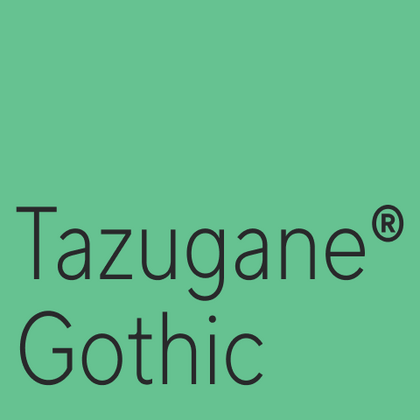
Шрифты похожие на Tazugane® Gothic
В этой подборке наши гарнитуры-альтернативы полностью заменят шрифт Tazugane® Gothic. Если вам близок его гибридный характер, обратите внимание на наши версии — они сохраняют фирменные черты — асимметричные кривые и динамичные пропорции. Эти альтернативы идеальны для проектов на стыке культур: брендинг с восточной эстетикой, интерфейсы международных сервисов или упаковка премиум-товаров.
Если вы устали от «заезженных» шрифтов и ищете гарнитуры, похожие на Tazugane® Gothic, ознакомьтесь с нашими лучшими альтернативами Tazugane® Gothic. Это шрифты, которые имеют близкие характеристики, но в то же время обладают новыми уникальными особенностями дизайна. Например, относятся к той же категории шрифтов, подходят для тех же целей и имеют похожие черты, но отличаются в деталях или пропорциях.
Найдите отличную замену Tazugane® Gothic и попытайтесь имитировать похожее настроение, передать нужное вам ощущение, используя его в своих проектах. Каждый шрифт, представленный на этой странице, является двойником шрифта Tazugane® Gothic, фактически его полным аналогом.
TT Chocolates — изящный гуманистический гротеск сo сбалансированными пропорциями, близкими к классическим. Шрифт с приятным дружелюбным характером, который интуитивно воспринимается как что-то знакомое.
TT Ricordi Greto — неконтрастный флорентийский гротеск с динамичными пропорциями. Это единственный гротеск среди антикв в коллекции TT Ricordi, при этом в нем сохранились едва заметные засечки, отсылающие к прототипу.
TT Firs Neue — скандинавский гротеск, сочетающий выразительные графические элементы с универсальностью использования. Мы проанализировали каждый контур и графический элемент. Пересобрали шрифт заново, чтобы сохранить лучшее и исправить необходимое.
TT Fellows — гуманистический гротеск с механистическими мотивами. Открытые формы, дружелюбно-нейтральный характер тонких весов и ещё более мягкий характер в жирных начертаниях.
TT Ramillas — стильная и современная антиква. Включает уникальные декоративные начертания и буквицы с цветочным орнаментом.
TT Octosquares — октагональный гротеск с футуристическим характером. Этот шрифт отличается геометричностью и своеобразной «мозаичностью»: он как бы собран из отдельных фрагментов, что проявляется и в мельчайших деталях.
TT Firs Text создавался на основе обновленной в 2023 году гарнитуры TT Firs Neue. Мы сохранили эстетику скандинавского минимализма, но полностью перерисовали все выразительные элементы, сделав их более мягкими и традиционными.
TT Norms® Pro — один из самых востребованных шрифтов студии, выбор известных мировых брендов. Более трёх переизданий за семь лет, первые строчки на MyFonts, десятки кастомизаций. Это «рабочая лошадка», которая станет незаменимой базой любой шрифтовой коллекции.
TT Commons™ Pro — один из самых востребованных шрифтов студии. Сфера его применения практически безгранична! Беспроигрышный вариант для тех, кто ищет стильный и функциональный базовый шрифт для любых проектов.
TT Hoves Pro — скандинавский гротеск с нейтральным, но в то же время узнаваемым характером. Это удобный и функциональный, при этом стильный и эстетичный инструмент для дизайнеров. Такой шрифт позволит вам решать множество разноплановых задач!
TT Supermolot Neue — непобедимое оружие в борьбе за стиль! Это технологичный модульный гротеск с футуристическим настроением и мощным функционалом. Шрифт идеально подойдёт для оформления компьютерных игр и множества других проектов.
TT Firs Neue — сбалансированный гротеск со скандинавскими мотивами. Это выразительный и привлекательный, при этом лаконичный и универсальный в использовании шрифт. Переиздан дважды, чтобы быть безупречным.
TT Rounds Neue — мягкий и дружелюбный шрифт, который умеет быть разным. В тонких начертаниях он выглядит минималистично и нейтрально. В жирных же — «надувается» и округляется, приобретая инфантильные черты.
TT Fors — тот самый шрифт «для всего». Это стильный, лаконичный и функциональный геометрический гротеск с выверенными формами. Его можно использовать и в интерфейсах, и для создания акцентов.
TT Ramillas — стильная и современная антиква, которая украсит любой проект. Уникальные декоративные начертания и буквицы с цветочным орнаментом помогут создать неповторимый дизайн. Шрифт уже используется на 3000+ сайтах во всем мире, а также отмечен наградой Modern Cyrillic.
TT Corals — это современный гуманистический гротеск, который имеет очень много характерных исторических черт начала 20-го века. Шрифт хорошо подойдет для темы классической литературы или музыки, а также для других самых разнообразных творческих областей человечества.
TT Prosto Sans является шрифтовой гарнитурой на любой жизненный случай. Благодаря современным открытым гротескным формам, вы можете использовать гарнитуру почти для любой задачи.